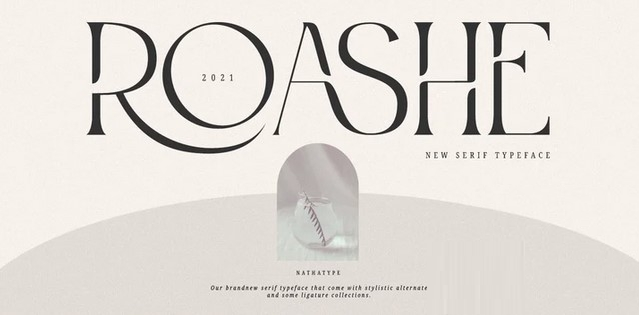
Название: Roashe Font (2021)
Один из самых элегантных, изысканных и в то же время сильных шрифтов.
Roashe создан для того, чтобы придать современный и стильный вид тому, что вы делаете. Этот шрифт содержит все символы в верхнем регистре. Хорошо подходит для заголовков, оформления плакатов, брендинга, логотипов и многого другого.
Roashe включает многоязычную поддержку, чтобы ваш брендинг охватил глобальную аудиторию. Вдохновите свою аудиторию, клиентов или гостей этим красивым и выразительным шрифтом.